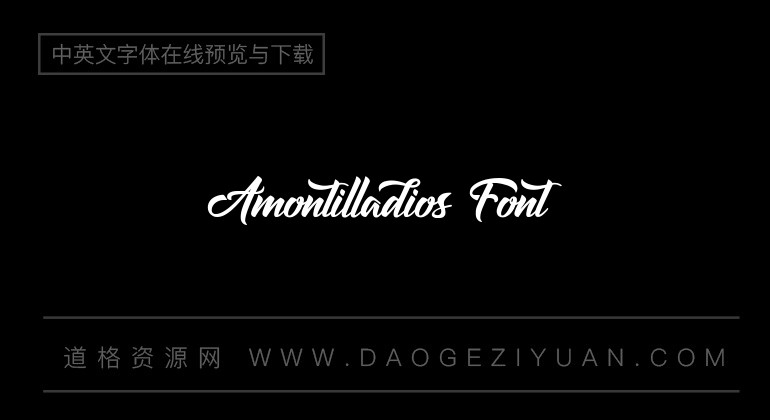
Amontilladios Font 是一种漂亮的字体,广泛用于设计和印刷方面。它的可读性非常好,字母线条流畅,具有现代感和优雅感。这种字体在设计名片、海报、传单、广告等方面很受欢迎。Amontilladios Font 适用于各种风格的设计,包括时尚、豪华、现代和传统等等。它可以用于标题、文本和标志等。总之,如果你想要一款时尚又漂亮的字体,Amontilladios Font 会是一个不错的选择。内容介绍
Amontilladios Font是一款非常不错的手写艺术字体,具有很好的视觉感,适合于文化类的宣传设计、商业类品牌的广告和产品包装设计以及个性化文字排版等较多场景。